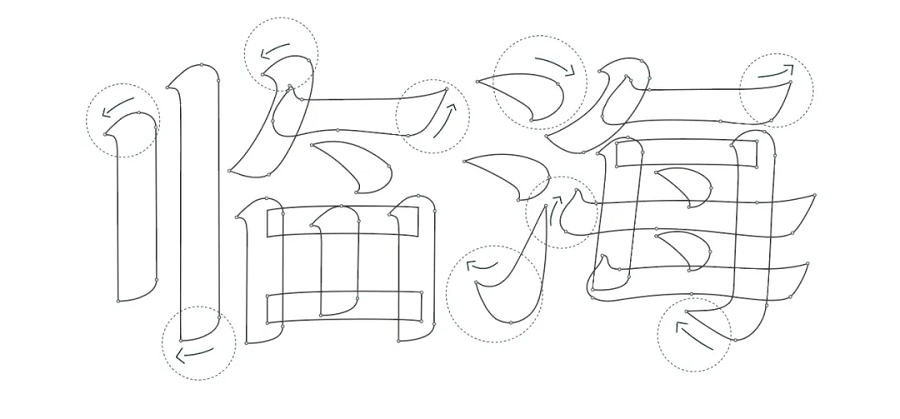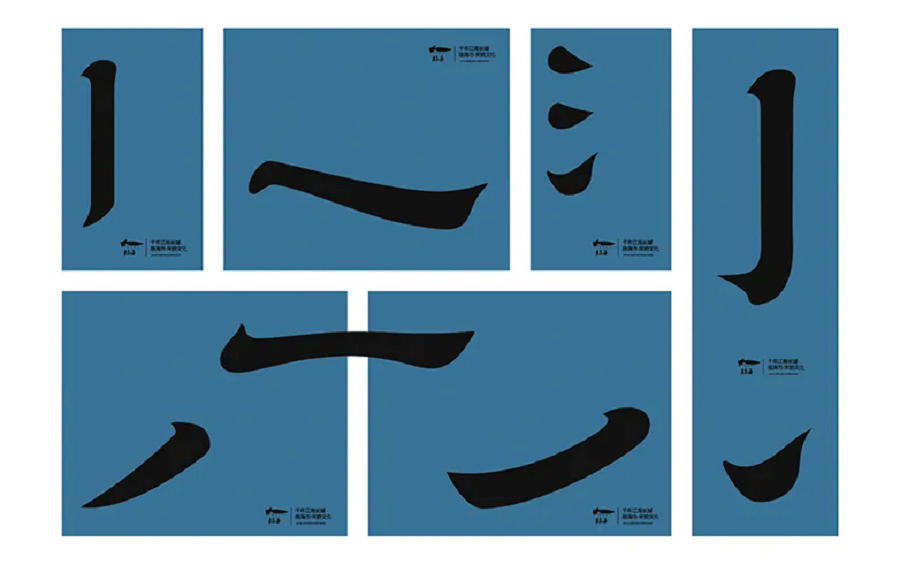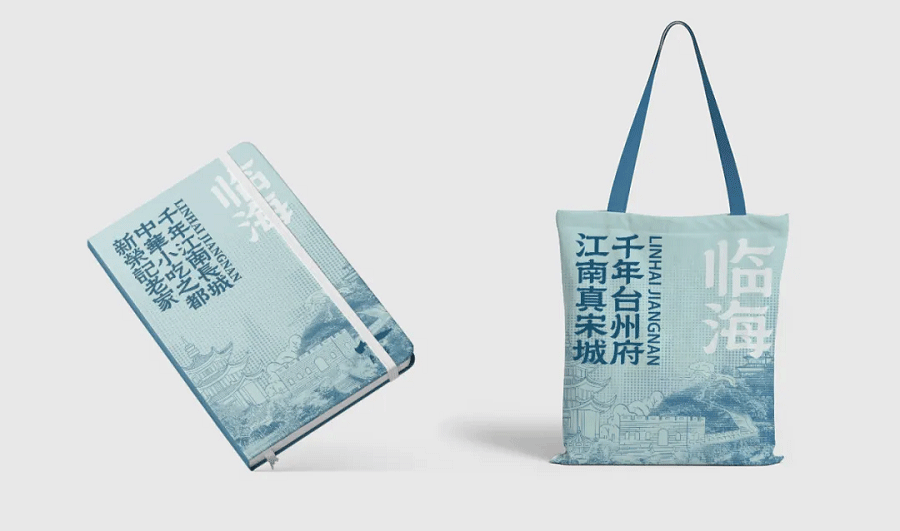
临海隶书是由浙江省临海市社发集团与乡立方字体团队联合推出的一款免费可商用城市专属字体,也是首款以城市命名的隶书字体。旨在通过融合传统隶书美学与临海地域文化特质,打造具有高度辨识度的城市文化符号。
临海隶书是由浙江省临海市社发集团与乡立方字体团队于 2023 年 12 月联合推出的一款免费可商用城市专属字体,也是首款以城市命名的隶书字体。
临海作为国家历史文化名城(1994年获批),拥有 1600 余年建城史,台州府城墙、紫阳古街等文化遗存丰富。而隶书兴盛于汉代,与临海城市起源时代(晋代建城)刚好相呼应,正所谓“一城化一字,一字如一城”,这款字体的诞生,正是为了打响”千年台州府,江南真宋城”的文旅品牌形象。
临海隶书打破了传统隶书过度扁平的局限,字形横向舒展,线条粗壮均匀、简洁规整,横画起笔锐利、收笔带雁尾,整体沉稳大气又兼具骨感温润。字体覆盖 GB2312 国标简体中文,包含常用汉字、字母、数字与符号,且免费商用,个人与企业均可合法用于印刷、网络、视频等场景。